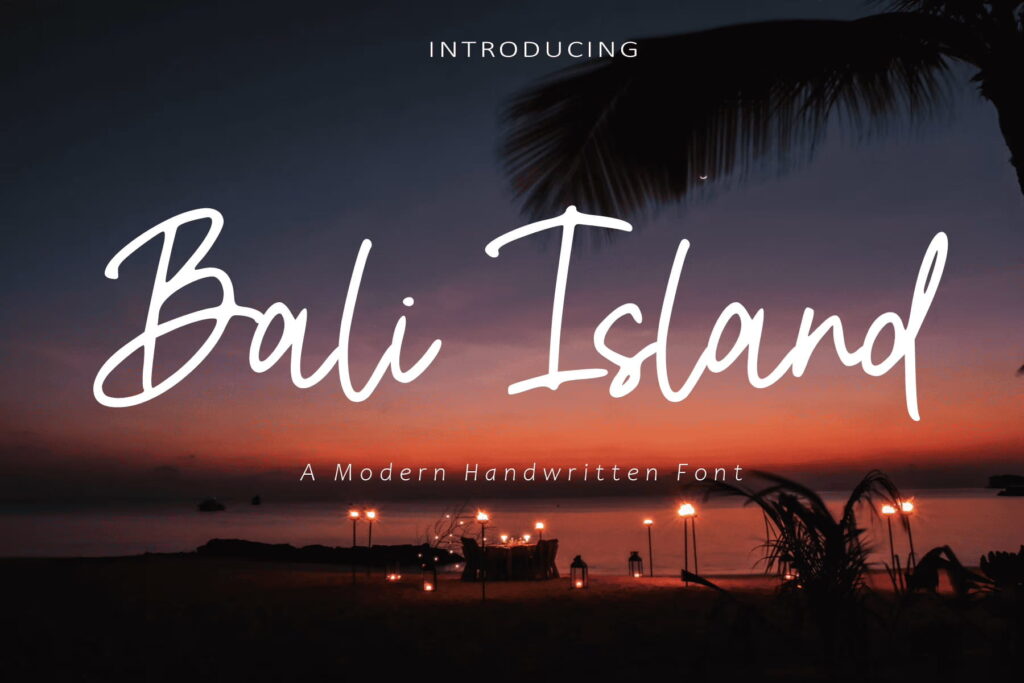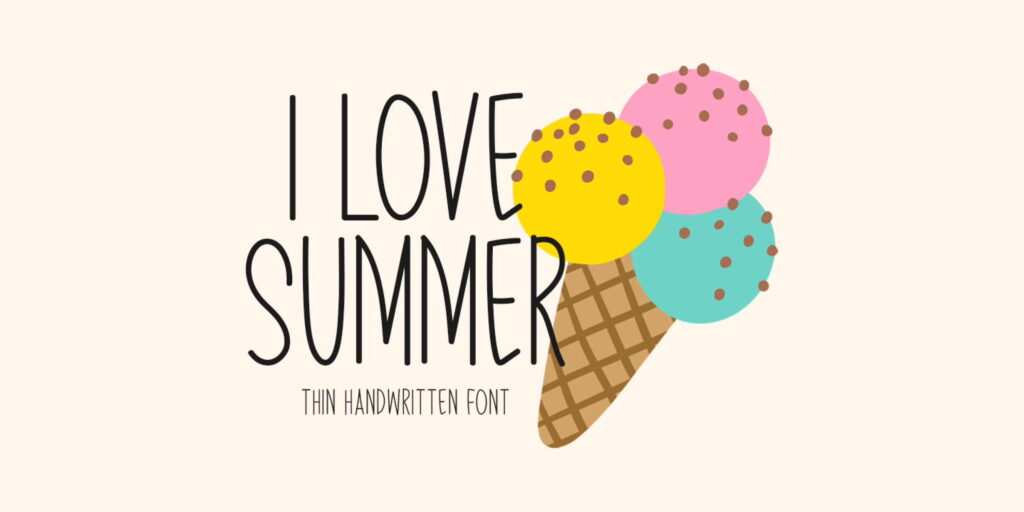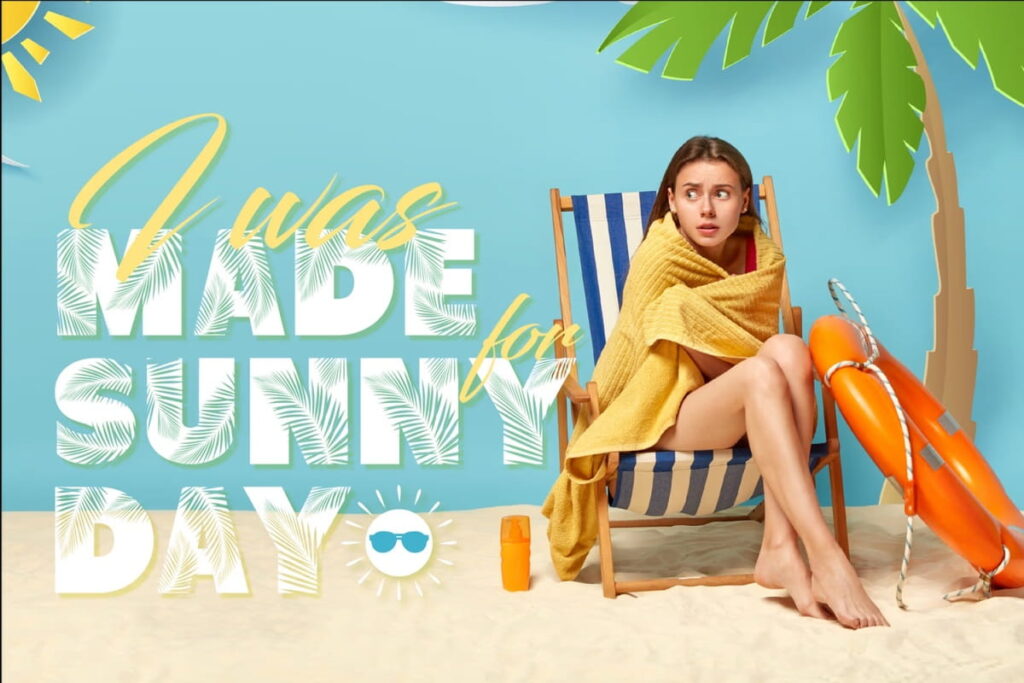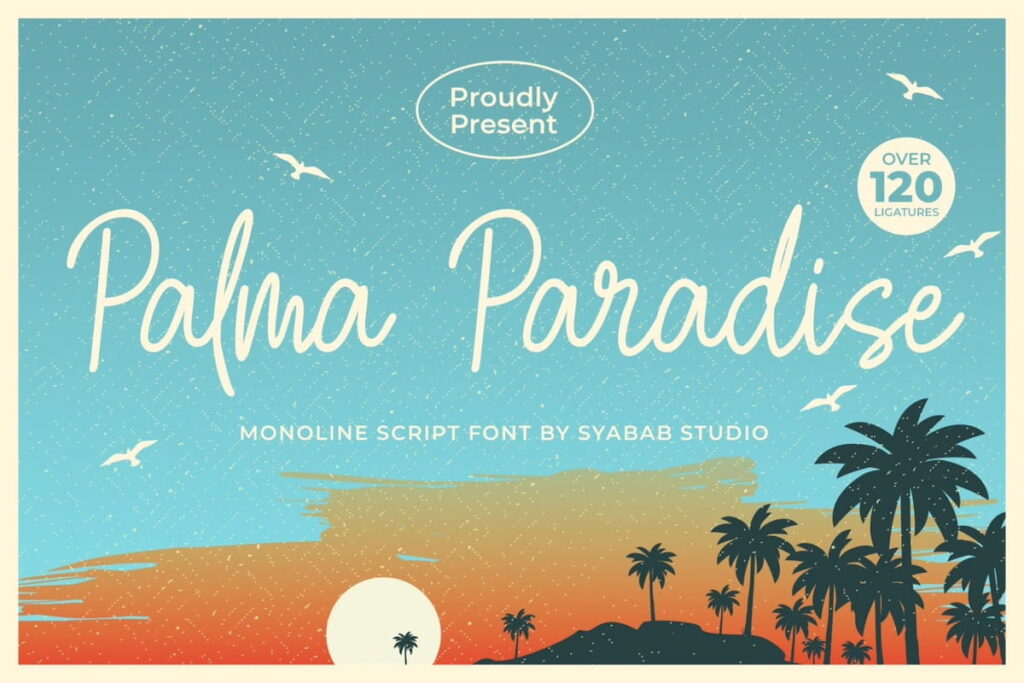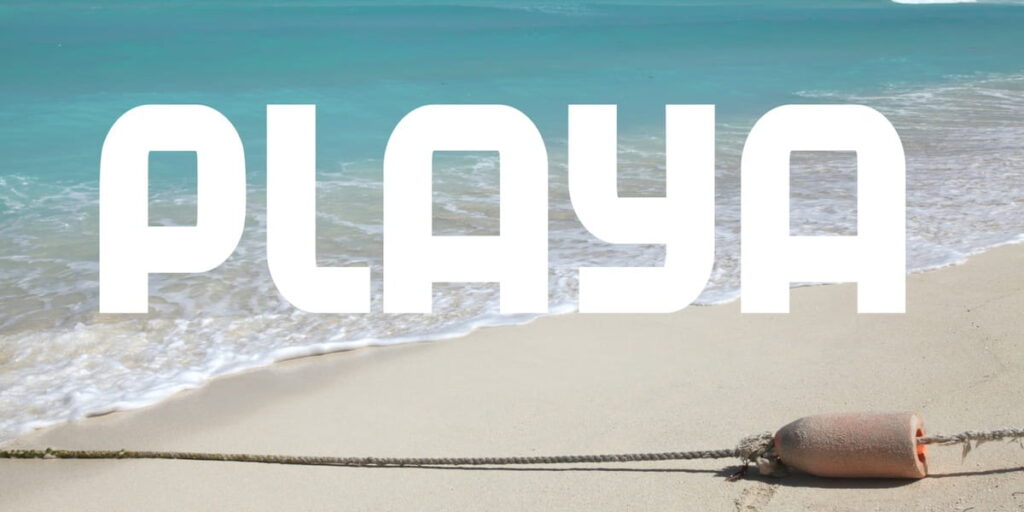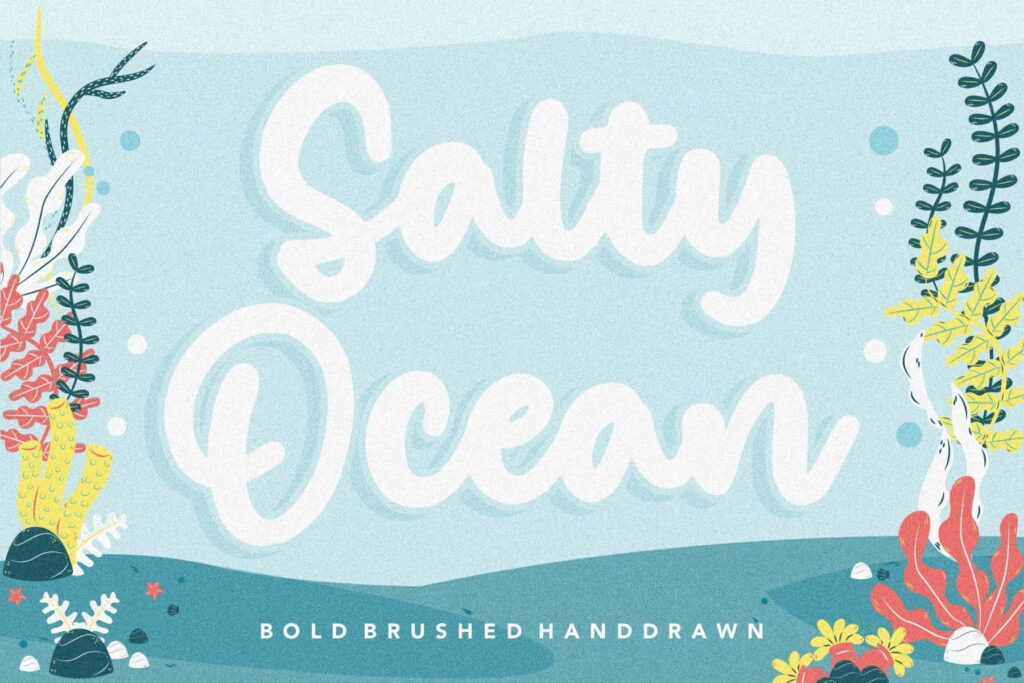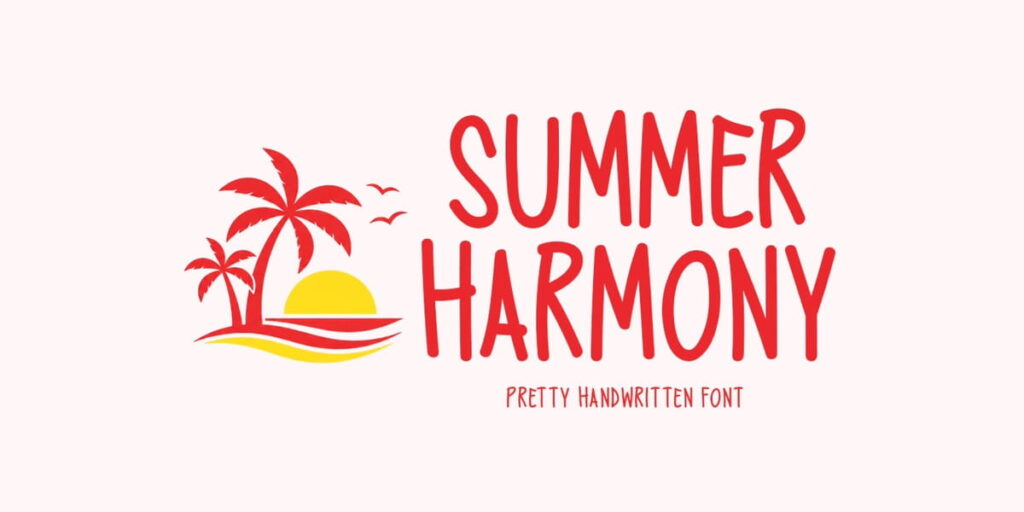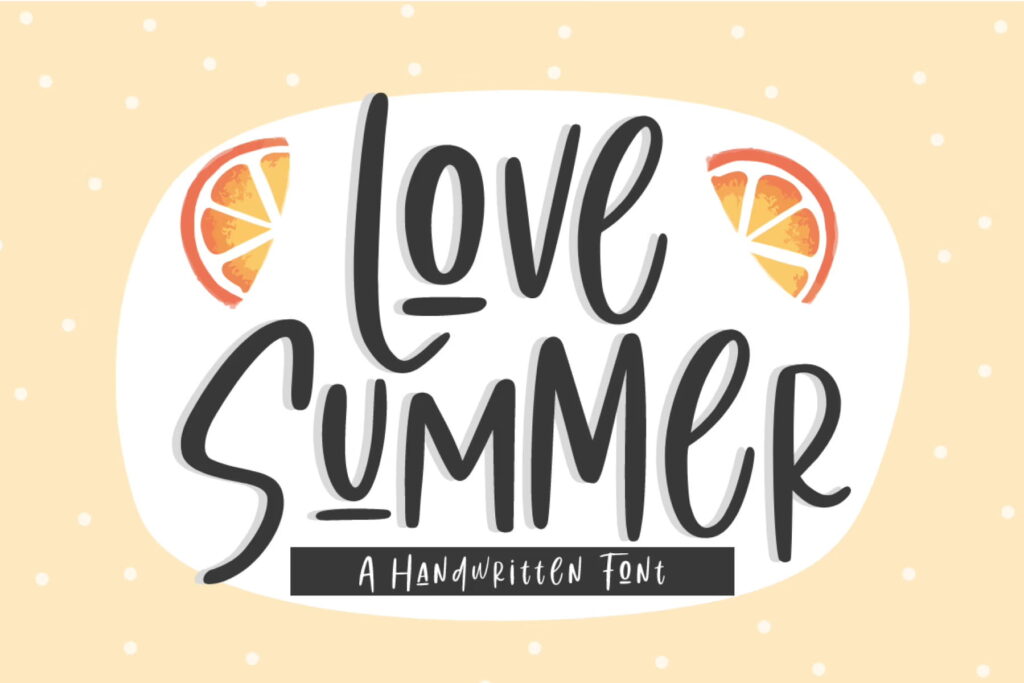
15 typographies à télécharger pour l’été
Si vous voulez donner immédiatement une hausse de vitamine D à votre visuel sans pour autant donner un coup de chaud à vos lecteurs, la typographie est la base de la communication pour l’été !
En effet, une typographie pertinente vous évitera de surcharger votre visuel et de mettre en valeur votre message de façon subtil. Mais il faut évidemment maîtriser les dessous de la typographie avant de faire monter la température !
1. Milkshake
2. Love summer
3. Summer Harmony
4. Summer handwriting font
5. Palm Leaf
6. Palma Paradise
7. Pines Black
8. Phelix Boomgartner
9. Sea Breeze Signature Script
10. Ocovilla
10. Playa
11. Forever Summer
12. Bali Island
13. I love summer
14. Ocean SIX
15. Salty Ocean
Comment choisir une typographie pour l’été ?
Quand on pense à l’été, on pense immédiatement à la saison du renouveau. Vous pouvez commencer par donner une dimension tendance à votre design en utilisant intelligemment ce qui se fait à la mode en matière de typographie. L’idée est de surprendre le public, mais aussi de le conforter dans un imaginaire fun et revitalisant.
Les typographies qui valorisent l’empâtement ou encore avec des traits épais sont à privilégier pour donner un aspect d’abondance, une certaine chaleur et une convivialité au message.
Et s’il y a bien une chose à savoir en été, c’est que tout est permis ! Osez les polices surdimensionnées ! Une typographie surdimensionnée permet de mettre le texte au centre de la création graphique : l’effet vitaminé sera au rendez-vous ! Cela pourra offrir à votre message cet enthousiasme qui représente l’été.
Le contraste est aussi un élément essentiel pour votre police d’été : jouer sur la diversité des caractères. Il ne faut pas hésiter à laisser des espaces blancs : l’été est aussi la saison où on fait des pauses, on se ressource, on prend le temps et on s’accorde de l’espace pour soi.
N’oubliez pas qu’une police d’écriture est modifiable à l’infini : vous pouvez étirer horizontalement ou verticalement votre typographie.
Mettez en forme l’été qui vous fait rêver !
Quels éléments permettent d’identifier une police d’été ?
On identifie une typographie qui inspire l’été quand elle joue volontiers sur les couleurs en employant par exemple des dégradés de couleurs et la luminosité des caractères. Pensez au soleil, à la mer et à toutes ces nuances de couleurs qu’offre l’été.
De plus, tous les effets de transparence applicables à la typographie peuvent donner ces impressions de lumière. C’est exactement ce qu’on veut retrouver dans une typographie d’été.
Les éléments qui permettent des associations innovantes avec l’italique donnent un effet de mouvement idéal pour la période estivale. Dans cet esprit, on peut voir certains graphistes jouer avec l’alignement et l’ordre des lettres dans leur typographie. Certains créateurs vont jusqu’à courber directement le texte pour mettre le mouvement au centre de leur création. On remarque tout de même que la tendance de la typographie de l’été conserve majoritairement un style épuré.
On retrouvera néanmoins dans les créations graphiques, des typographies qui n’hésitent pas à intégrer directement des images ou des textures qui représentent l’été (image plage, texture de sable, mer, etc).
L’été, c’est aussi le moment où on sort les romans pour lire sur la plage. Cela peut expliquer pourquoi les typographies manuscrites ont une belle position dans les créations graphiques d’été. La typographie manuscrite offre un aspect décontracté et une légèreté dans le message incomparable. On s’éloigne de la lourdeur des contraintes professionnelles pour se laisser aller à une forme de poésie de l’instant présent. La typographie manuscrite est parfaite pour transmettre ce carpe diem estival !
Notre astuce pour votre typographie
Maintenant que vous savez comment mettre un peu d’été dans votre typographie : à vous de jouer !